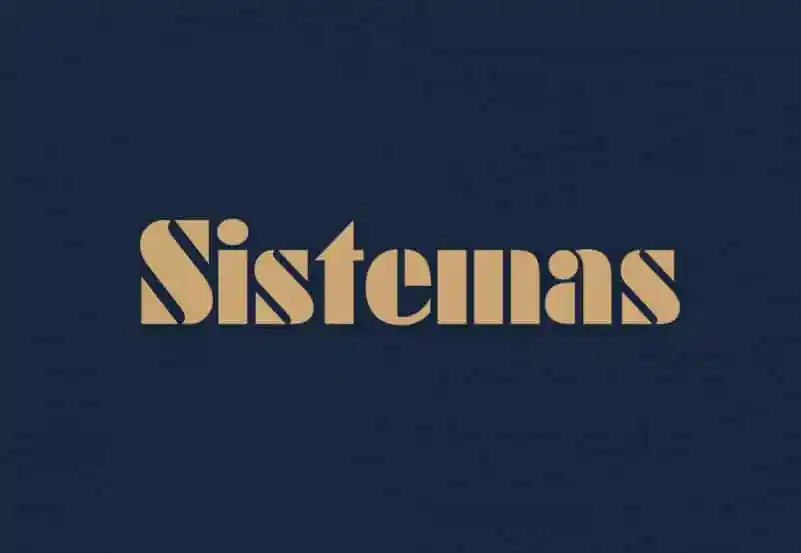
Sistemas Display Font é uma elegante tipografia contemporânea projetada especificamente para títulos, embalagens e identidades visuais. Suas linhas retas e forte contraste de traço dão ao tipo um visual arrojado e forte, tornando-o perfeito para nomes de empresa ou logotipos, bem como texto moderadamente longo que é usado em websites, citações, convites, cartões de visitas, folhetos e embalagens. Como uma seleção agradável para títulos ou logo e textos médios a longo, Sistemas Display Font oferece um look moderno e sofisticado, capaz de destacar seu design em qualquer aplicação visual. Aliás, é o tipo certo quando você precisa criar uma identidade visual única e profissional.